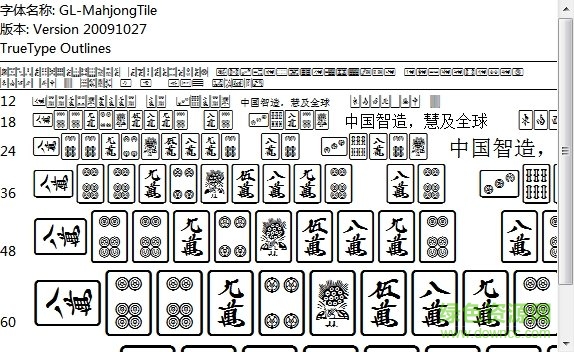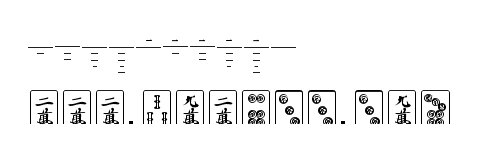
麻将牌字体
麻将游戏字体是一款相当有艺术感的特色符号字体,收录了最全的麻将牌字体,生动还原了麻将的牌面设计,让玩家引用麻将图案更加方便,快来绿色资源网试试吧!
麻将牌字体特色
GL-MahiongTile麻将字体,可以输出珠算字体符号,长牌符号,麻将符号。
麻将牌面字体
麻将是什么字体
麻将上刻的字根据不同地方或者做工不尽相同。不过使用最广泛的是楷体(行楷)字体。也有小部分使用魏碑体或隶书。